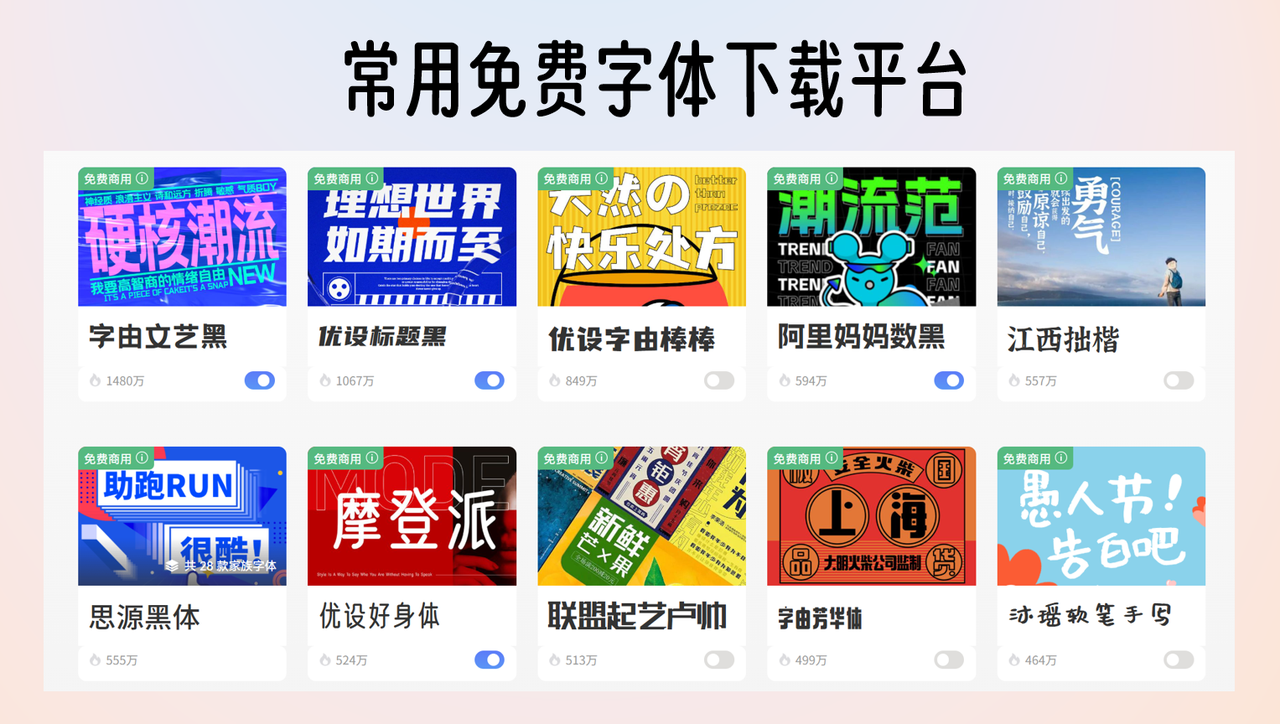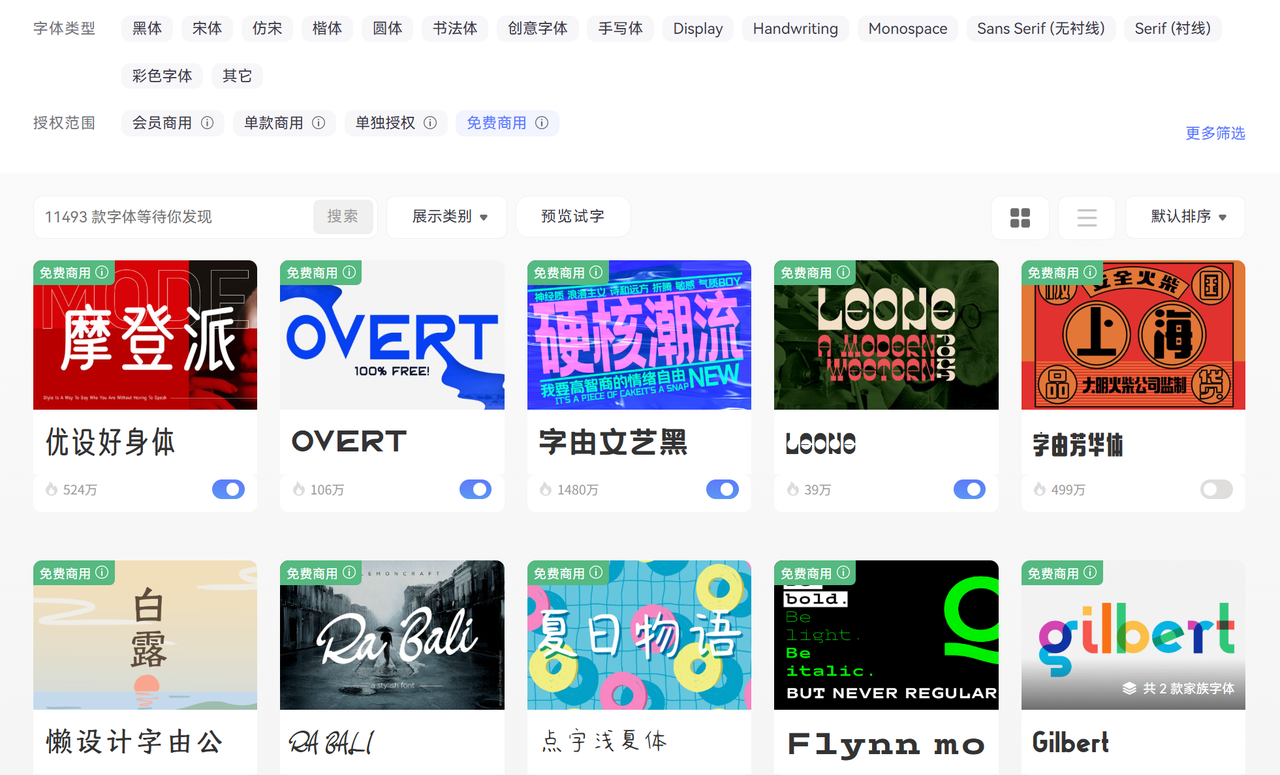
常用免费字体下载平台有哪些?推荐这8个给你
如果说只推荐一个工具,我一定会把票投给“字由”。它更像是一个字体管理软件,而不是传统的下载网站。
你不需要把字体下载、安装到电脑里,直接通过它的客户端,在PS、AI、Sketch等软件中就能点击即用。它清晰地标注了哪些字体可以免费商用,哪些仅限个人使用。对于我这种平时排版量很大的人来说,字由最大的好处就是省去了我频繁清理电脑系统字体的麻烦。
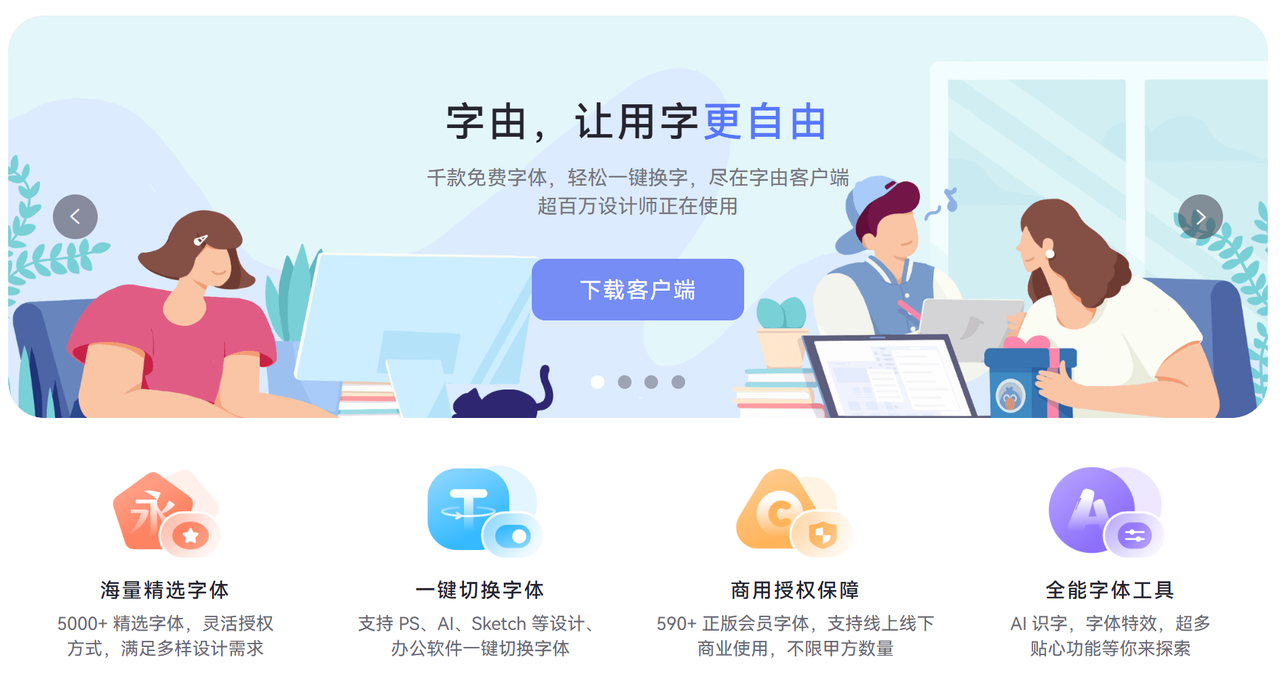
Google Fonts
Google Fonts 是我最信赖的国际化平台。它最大的特点是“纯粹”和“开源”。
这里的字体全部基于开源协议,这意味着无论是做个人博客、商业网站还是平面海报,你基本不用担心版权纠纷。如果你需要一套简洁、现代的无衬线字体,或者具有设计感的标题字,这里是首选。虽然界面是英文,但它的筛选功能做得非常人性化,即使英语不好,通过标签也能快速定位到想要的风格。
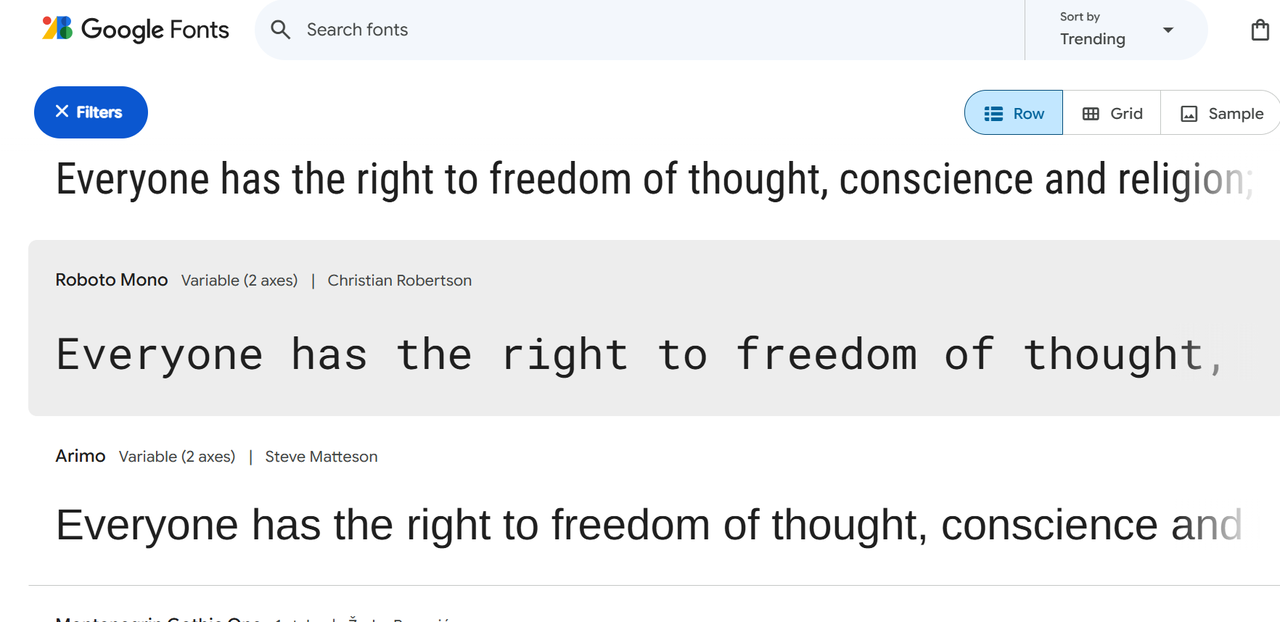
阿里巴巴普惠体
提到中文商用字体,不得不提“阿里巴巴普惠体”。这是阿里巴巴为了解决商业设计中字体授权昂贵的问题,专门推出的开源字体。
我非常喜欢用它来做大标题,因为它的笔画非常稳重,无论是屏幕显示还是打印,视觉清晰度都极高。作为一个设计师,我深感这种“大厂开源”给行业带来的便利。只要你遵循它的开源协议,无论是电商详情页还是企业画册,都可以放心使用。
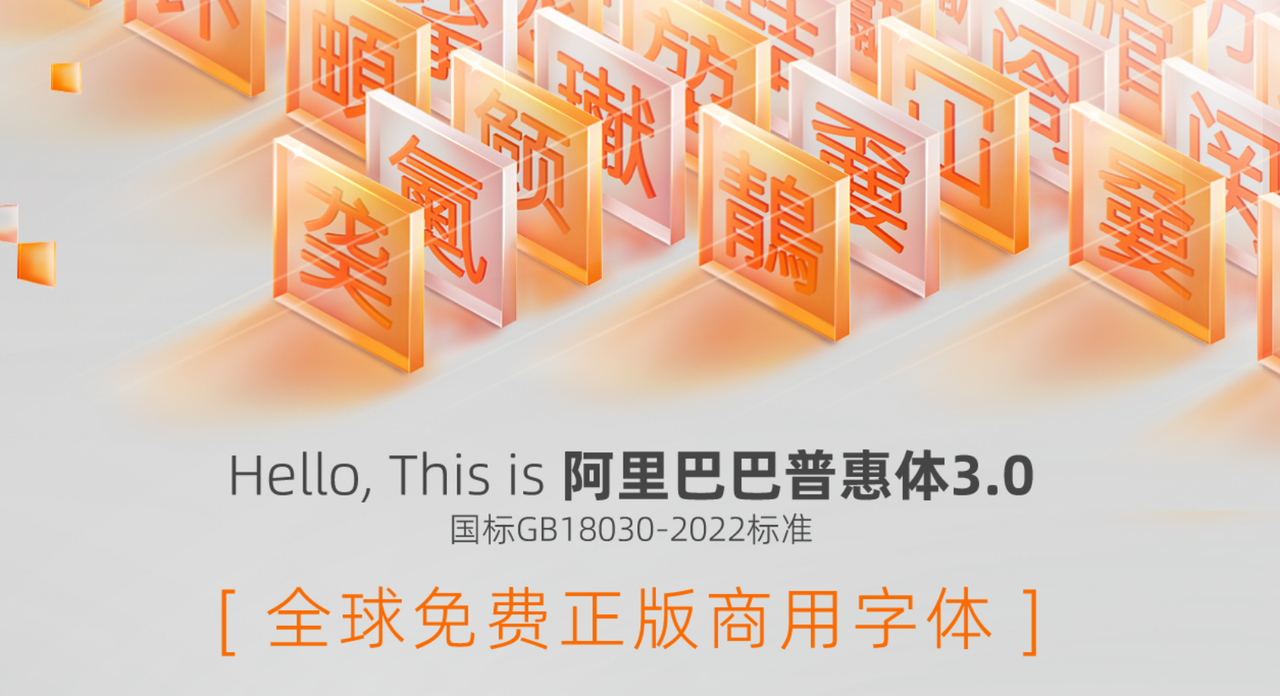
思源系列
我喜欢它的原因是它的字重非常丰富。从极细到极粗,每一款都能找到对应的使用场景。如果你在做一套复杂的排版,需要区分层级,思源系列的一整套家族字体能完美覆盖你的需求。它不仅免费,而且在各种设备上的渲染效果都非常平滑。
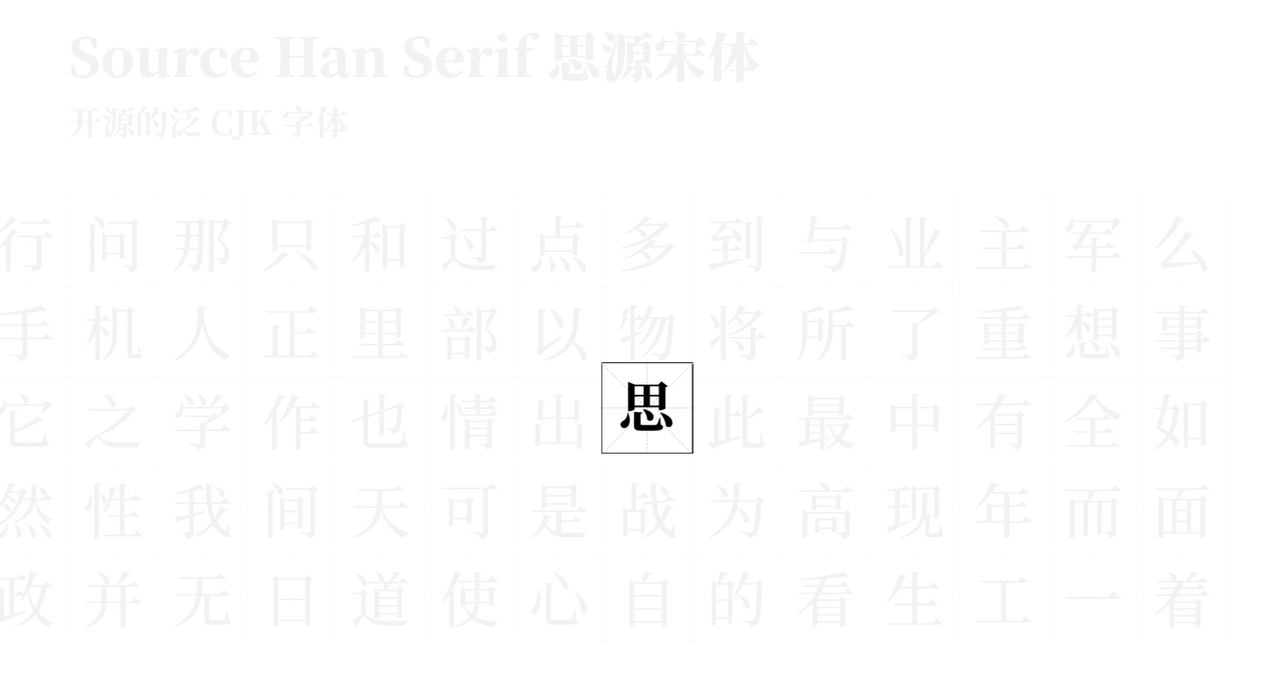
猫啃网
这个平台的风格非常接地气,它不仅提供下载,还会细心地标注这款字体的作者是谁、协议是什么。很多小众的、独立设计师发布的免费字体,我都是在猫啃网第一时间看到的。如果你不想在一个个品牌官网之间来回跳转,直接盯着猫啃网的更新就足够了。
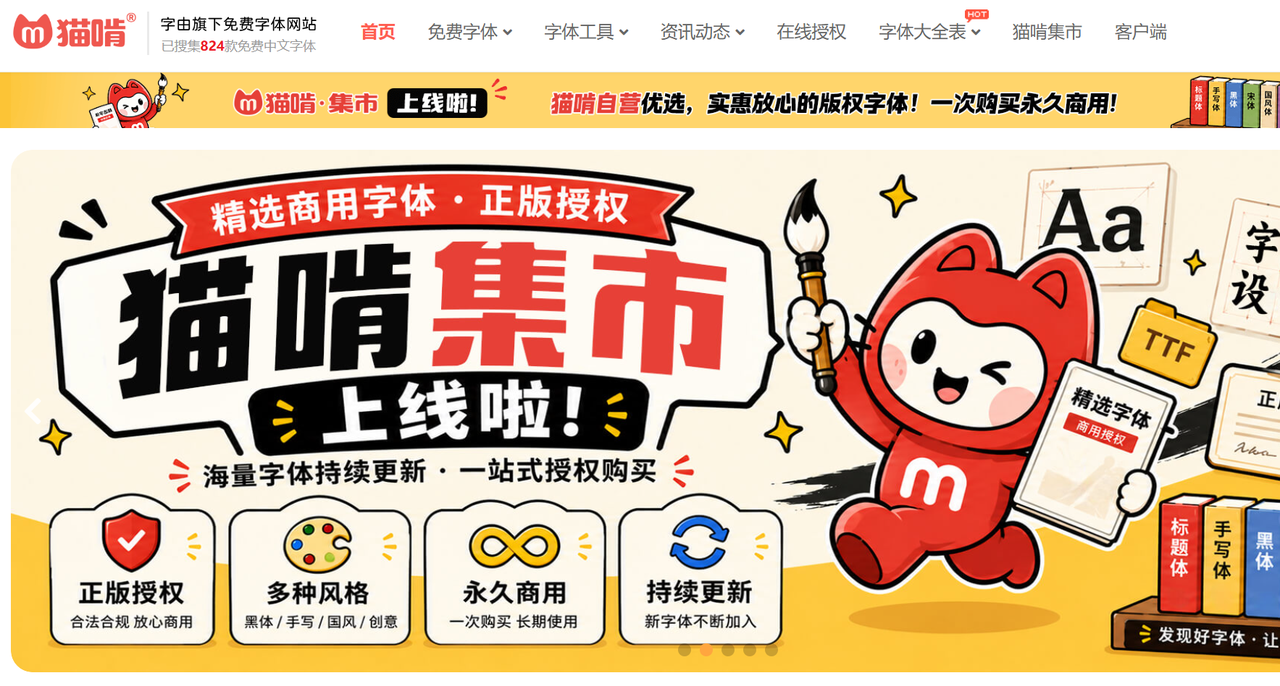
DaFont
如果你的项目需要一些个性化的英文装饰字体,比如哥特风、手绘风、像素风,DaFont 是全球这类资源最丰富的聚集地。
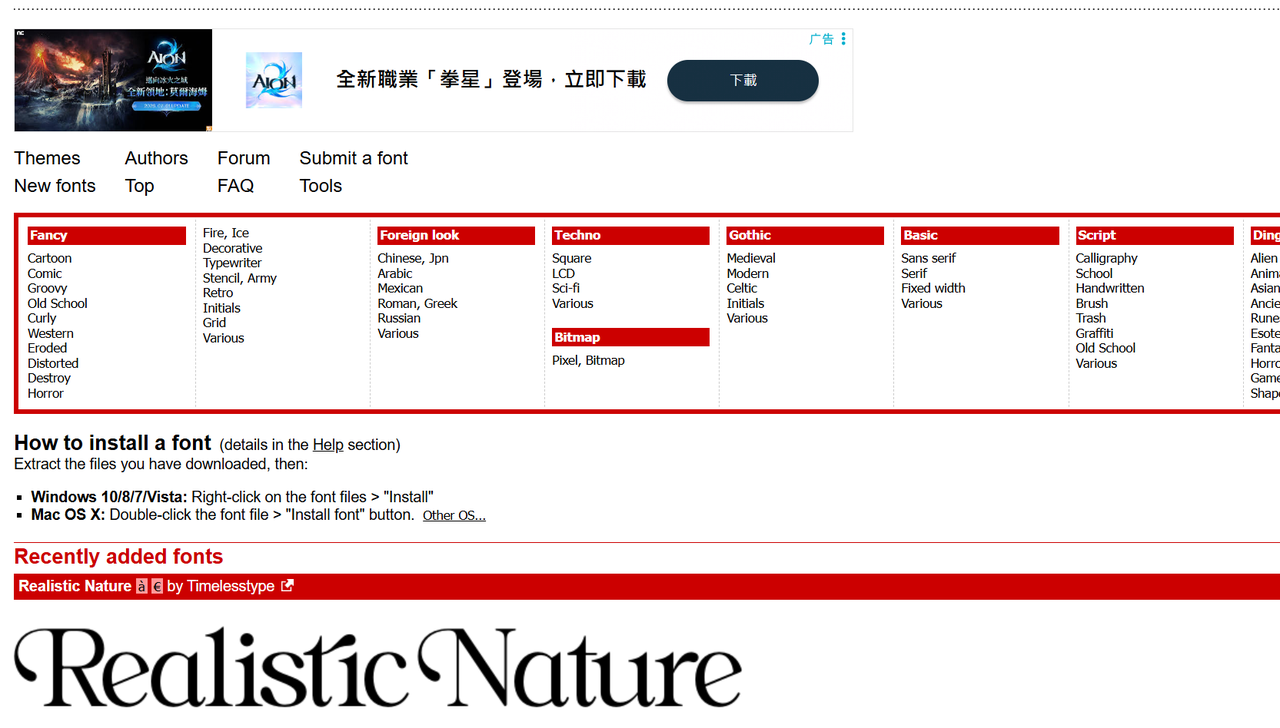
站长素材字体
虽然有些传统,但“站长素材”在资源整合上非常扎实。很多时候我们要找一些老旧的系统字体或者常规中文字体,这里都能搜得到。
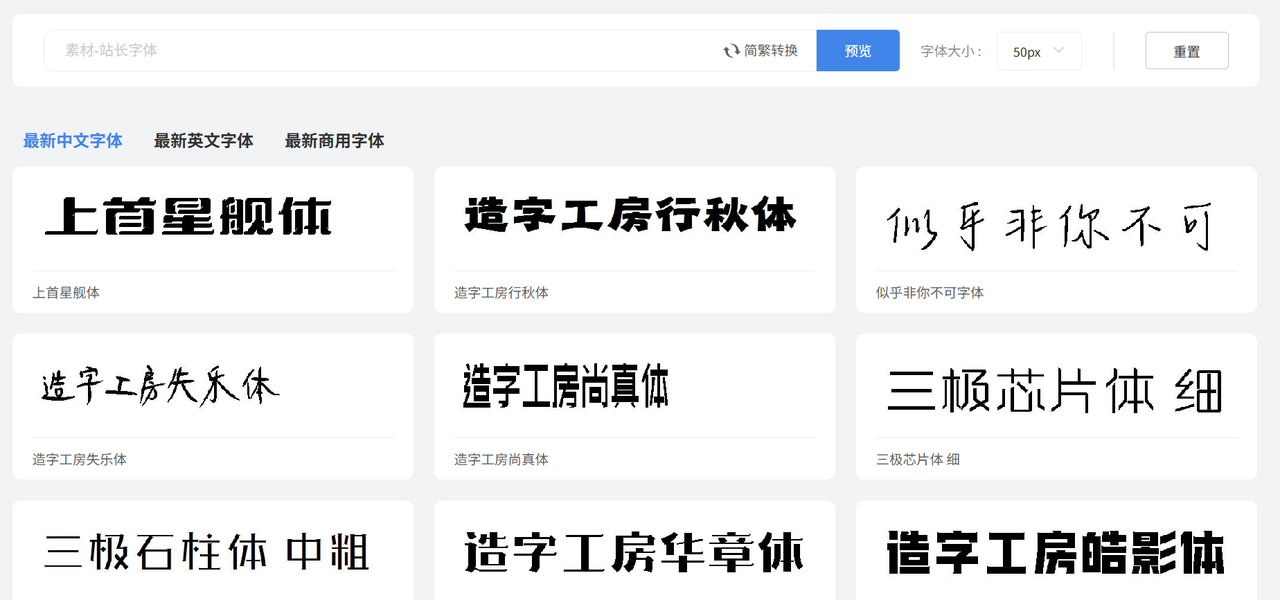
100font
这是一个非常纯粹的平台,顾名思义,它整合的内容基本都指向“免费商用”。
我推荐它的原因在于它的分类逻辑很强。它会根据“黑体”、“宋体”、“书法”进行详细划分,并且在每个字体的下载页都会醒目地提示“是否可免费商用”。对于担心版权问题的初学者来说,这个平台能最大限度地消除你的心理负担。